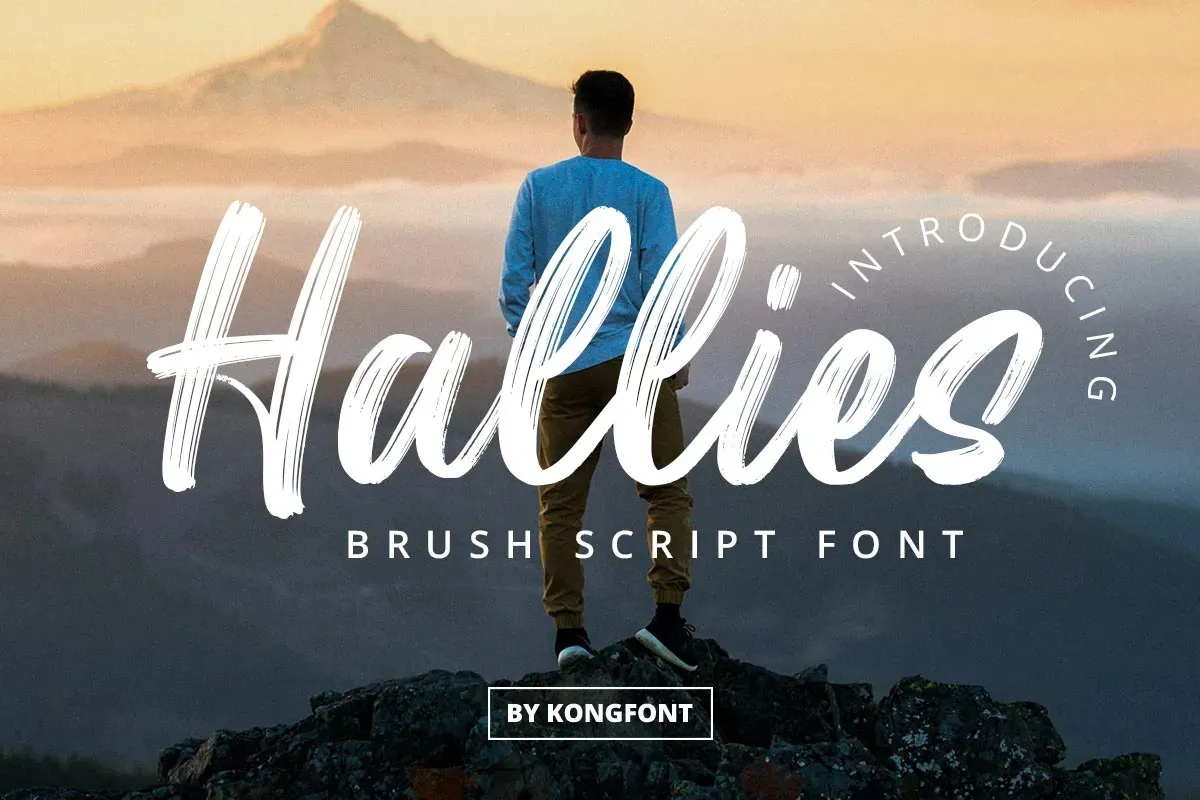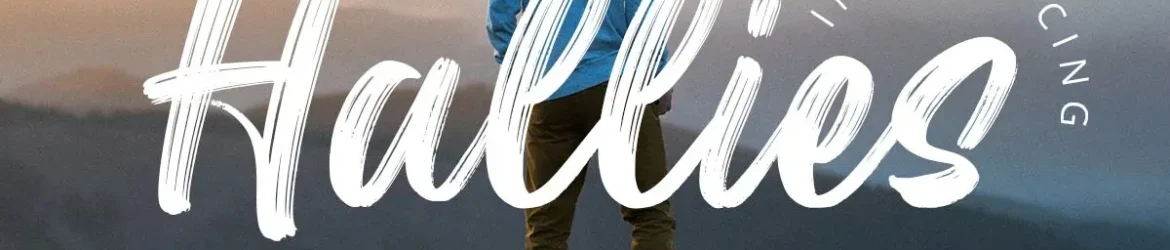
Hallies é uma nova tipografia moderna com traços artesanalizados que traz uma base de linha irregular para uma abordagem contemporânea do design, ideal para uso nas aplicações visuais como roupas, convites, títulos de livros, materiais de escritório, citações, marca identidade, logotipos, camisas, embalagens e panfletos. Com letras maiúsculas e minúsculas, suporte multilinguagem para números e pontuação, a Hallies se destaca como uma opção versátil para o design de textos em qualquer situação criativa. Seja para um logotipo que representa sua marca com estilo único ou para criar um layout de postura impactante, a Hallies é perfeita para quem procura tanto elegância quanto originalidade no seu trabalho gráfico.